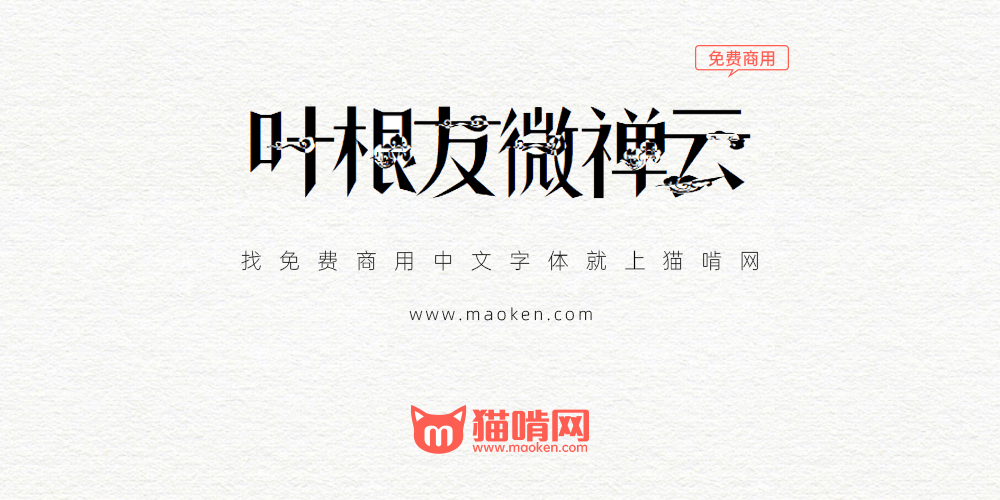
叶根友微禅云:禅修心道养性缠中有禅
字体作者:叶根友 (中国大陆) 字体字重:1个
从2019年08月01日起,为了感谢各粉丝的支持,我国字体设计师叶根友特别公开四款字体免费商用。这四款字体分别是 叶根友守中曲画叶根友微典体叶根友微禅云叶根友锐劲体
叶根友微禅云是一款非常有特色的字体,每个字型中都有一个云朵的图案在里面,看过来非常有个性。不过好像这个版本在PS中有点问题,在其它软件中则显示正常。不知道大家的PS中能不能正常使用。